近日,顺德书画篆刻家范国华入选“红色印记——庆祝中国共产党成立100周年全国篆刻作品展暨首届‘齐白石杯’篆刻名家提名展”,彰显出新时代的顺德艺术家传承、发扬中华传统文化的新气象。
“红色印记——庆祝中国共产党成立100周年全国篆刻作品展暨首届‘齐白石杯’篆刻名家提名展”由中国收藏家协会主办,特点是入选名家多,作品水准高。范国华人称“千字哥”,每日习书千字故得此绰号。研习书画篆刻近四十年,五体书法皆擅长,书风和润古雅,意韵脱俗,尤以隶书与小楷见长,形成了独特的空派书法艺术风貌而自成一家。
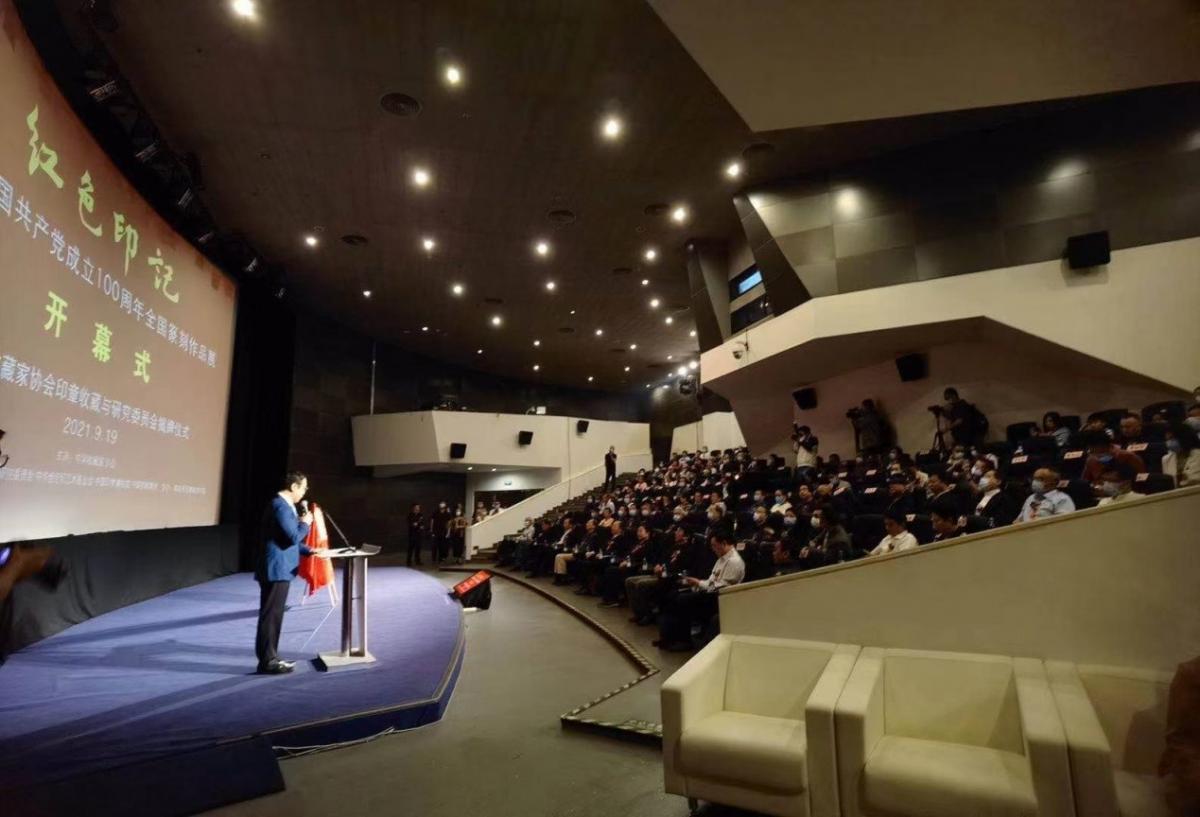
本次展览坚持主题精心打磨、评选精益求精、作品精雕细刻。展览主题是“红色印记”,将党史事件、名言美辞、新时代金句作为创作重点,以篆刻艺术形式向伟大的中国共产党献礼。组委会从1000多份来稿中,无记名的打分评选,最终选出入展作品118件。
展览充分考虑了不同地区、不同民族、不同年龄、不同风格的代表性。既有大中城市知名艺术家的大作,又有内蒙古、云南、西藏等边远地区篆刻新人新秀的佳作,旨在深化民族团结进步教育、铸牢中华民族共同体意识、加深各族群众对中国共产党的深厚感
范天原名范国华,字由之,号愚公。祖藉湖南常德。现定居佛山顺德。其书法篆刻作品曾获国际展、国展、省展等诸多奖项,二德居书画院院长、三人行古典吉他交流协会创始人。现为中国硬笔书法家协会会员,中国国际书画艺术研究会会员,香港国际书画家交流协会理事,深圳、武汉翠碧轩书画研究院客座教,授广东省书法家协会会员,佛山市书法家协会会员,顺德工艺美术家协会会员,顺德鉴藏家协会会员,顺德印社秘书长,大中华区艾菲奖评委(广告界的奥斯卡),尚都雕塑艺术馆艺术总监。
范天(范国华)先生、人称“千字哥”,每日习书千字故得此绰号。五体书法皆擅,浸淫其中近四十年,外师造化,中得心源。书风和润古雅,意韵脱俗。尤以隶书与小楷行世。隶书古厚遒劲,气象正大,人称“范隶”。小楷气韵高古、萧疏简淡,空灵有致,形成了独特的空派书法艺术风貌而自成一家。篆刻“印宗秦汉”,扎根传统,曾临近千多方秦汉印,对汉玉印情有独钟颇有心得。先生勤苦,步步正统。注重人品,学富和艺娴之修炼,游于艺者,首务品高再求学富,三须艺娴,真正领会学书要胸中有道义,又广以圣哲之学,书乃可贵。
范天(范国华)篆刻作品
范天(范国华)书法作品